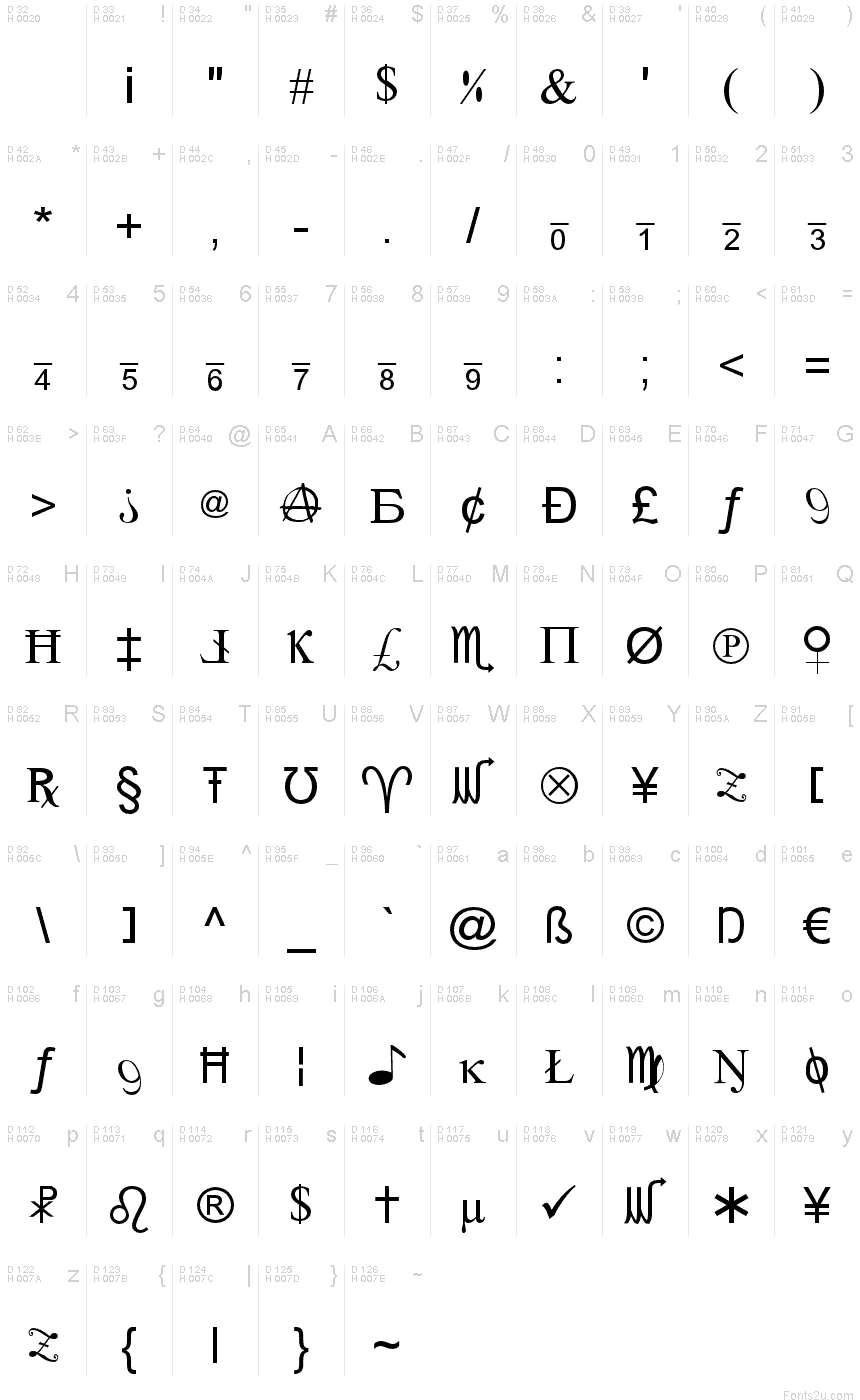
X-Cryption, бесплатный шрифт-дингбат от Iconian Fonts, превращает привычные буквы и знаки в зашифрованные символы с выраженной атмосферой техно-загадки. Круги, косые черты, двойные полосы и перекрестия повторяются в наборе, поэтому символы выглядят не столько декоративными, сколько намеренно закодированными — словно знаки из футуристической головоломки или секретного интерфейса.
Благодаря этому шрифт отлично подходит для графики игровых HUD, научно-фантастических плакатов, обложек альбомов, зинов и титульных карточек, где нужно быстро создать ощущение тайны. Как бесплатный шрифт, он лучше всего работает в коротких фрагментах — в логотипах, началах глав, монограммах или эмблемах фракций, — так как повторяющиеся кольцевые и пересекающиеся формы придают даже небольшим группам символов целостный закодированный вид.